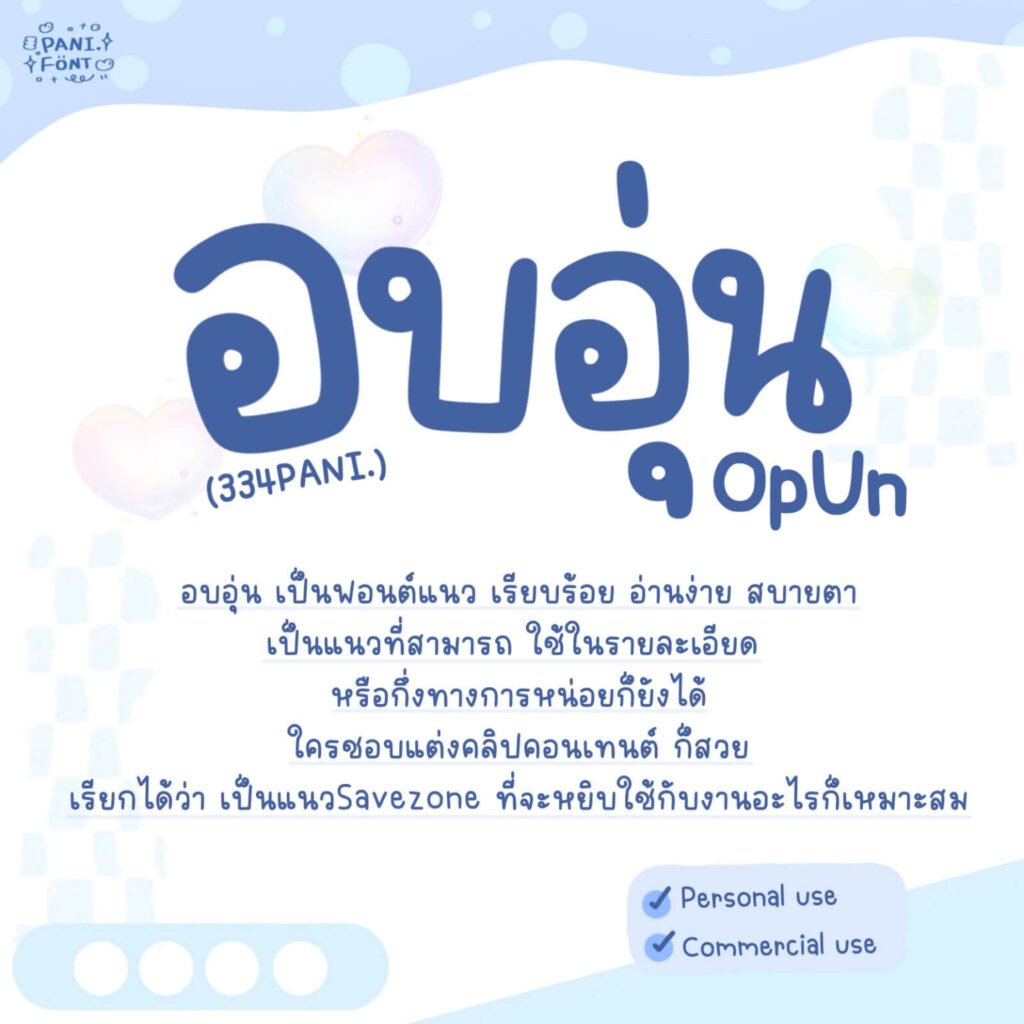
ฟอนต์ 334PANI.อบอุ่น (334PANIOpUn)
ฟอนต์ 334PANI.อบอุ่น (334PANIOpUn) ฟอนต์ 334PANI.อบอุ่น – โหลดทดลองใช้ฟรีตัว Demo อบอุ่น เป็นฟอนต์แนว เรียบร้อย อ่านง่าย สบายตา เป็นแนวที่สามารถใช้ในรายละเอียดหรือกึ่งทางการหน่อยก็ยังได้ ใครชอบแต่งคลิปคอนเทนต์ ก็สวย เรียกได้ว่าเป็นแนว Save zone ที่จะหยิบใช้กับงานอะไรก็เหมาะสมฟอนต์มี 3 ไฟล์ – น้ำหนัก บาง ปกติ หนาโหลดใช้ฟรีตัว Demo 1 ไฟล์...